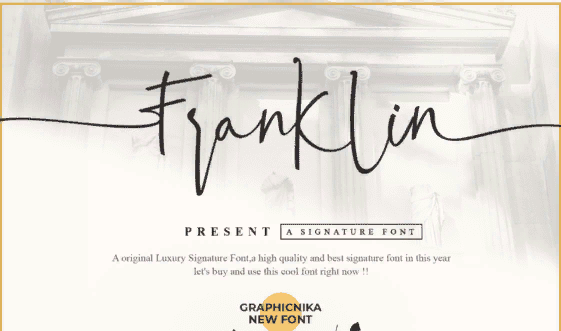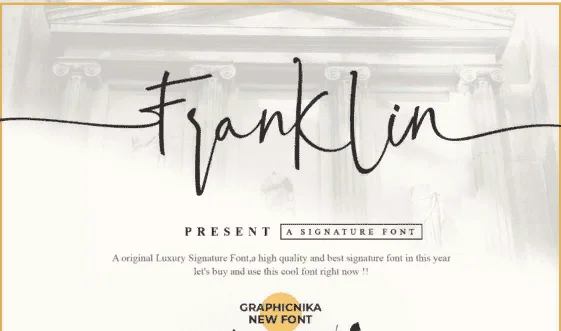
[Creativefabrica] Franklin Font (2021)
Название: Franklin Font (2021)
Franklin
- шикарный, изысканный шрифт, излучающий утонченность и элегантность.
Стильные чередования и лигатуры делают этот шрифт идеальным для любого проекта.